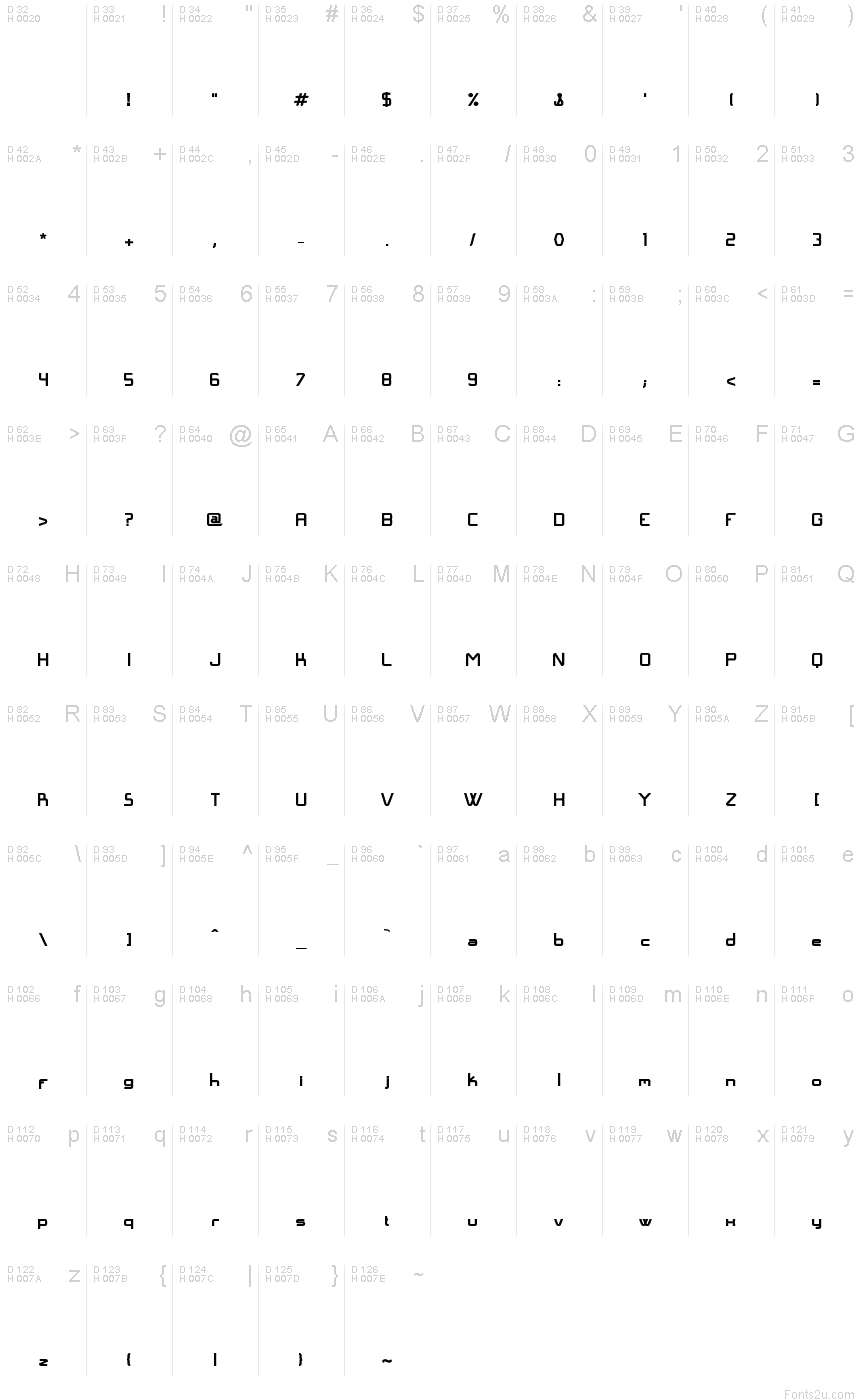
Langó Bold
Langó Bold è un font display gratuito caratterizzato da una struttura geometrica squadrata e angoli arrotondati. I suoi glifi utilizzano blocchi semplici e spazi interni aperti, con un ritmo fluido ed essenziale che conferisce al design un aspetto digitale e nitido, senza risultare troppo rigido.
Langó Bold è ideale per titoli di poster, loghi, banner per gaming, branding di app e brevi accenti editoriali dove la forma geometrica è protagonista. Si adatta perfettamente anche a insegne e packaging, poiché le sue forme compatte e coerenti permettono al nome di apparire come un elemento grafico unico e integrato, piuttosto che una semplice riga di testo.